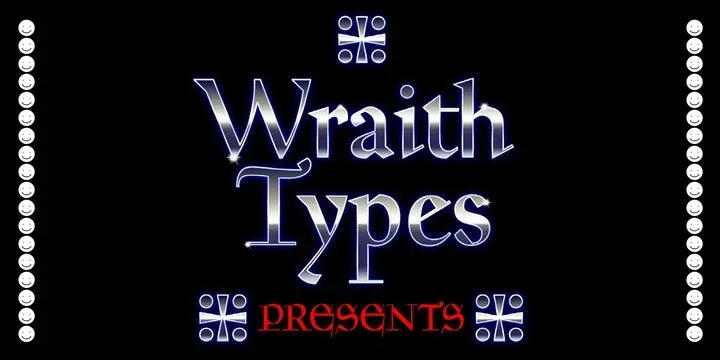
WT Mediaeval Font é uma elegante e forte fonte serif que transporta você para o mundo medieval, mas incorporando um toque contemporâneo. Desenvolvida originalmente no início dos anos 1920 pelo designer Goudy, esta fonte traz à tona as raízes antigas e transmite uma mistura inspiradora de elegância e força. Com seu formato medieval, o WT Mediaeval Font oferece um revival digital que mantém a essência antiga enquanto adquire uma aparição moderna. Ideal para projetos que buscam trazer harmonia ao belo do antigo e robustez no contemporâneo, esta fonte é perfeita para desafios de design que valorizam tanto a elegância clássica quanto o vigor atual. Seja você um designer ou web developer buscando um recurso gráfico que atende às suas necessidades, não hesite em explorar as possibilidades criativas oferecidas pela WT Mediaeval Font.